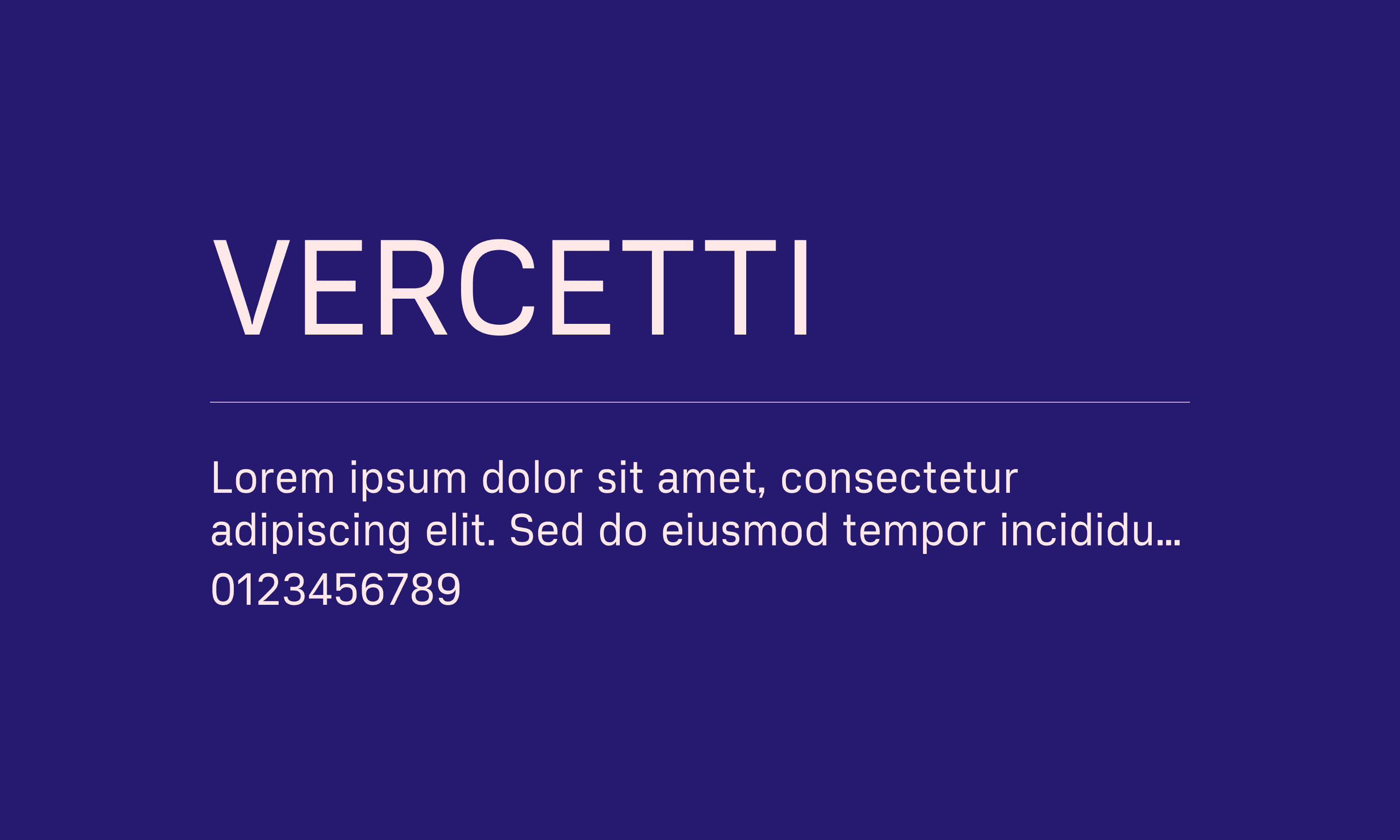
Vercetti
Vercetti 是一款现代的无衬线字体,设计风格独特、具有高辨识度,融合了简洁的几何线条和大胆的笔画对比。它的设计灵感源自经典的无衬线字体,但在形态上更加注重个性和现代感,适合用在需要高冲击力和独特视觉效果的设计项目中。Vercetti 字体非常适合品牌设计、广告、标题、海报以及其他需要吸引眼球的视觉内容。